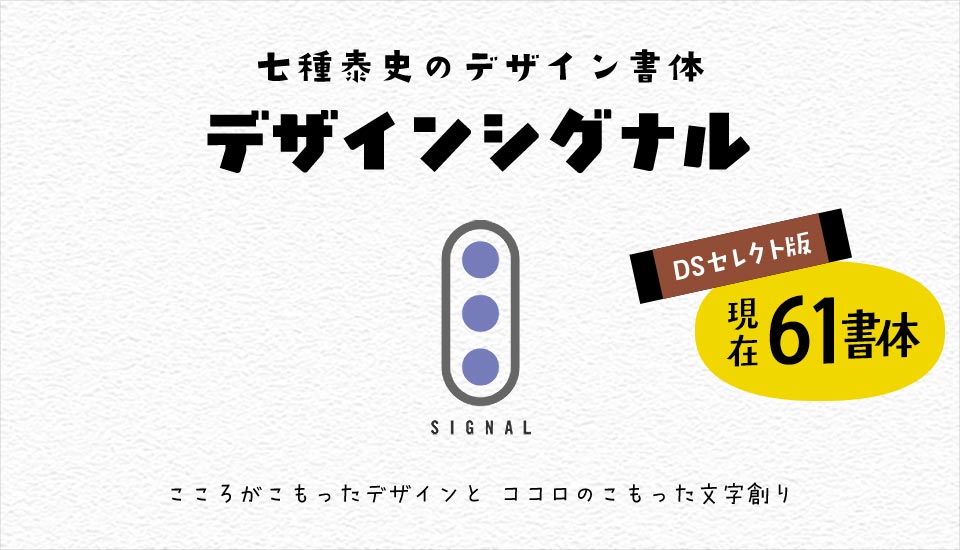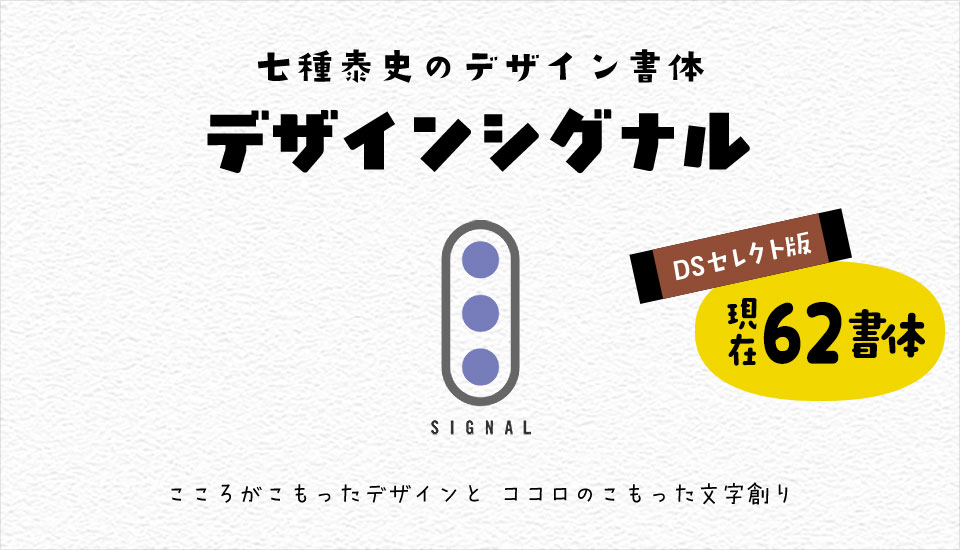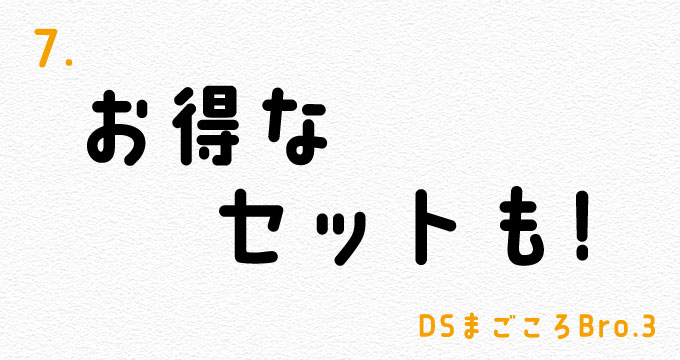
デザインシグナル・七種泰史のデザイン書体 DSセレクト版64書体
2026年秋の新書体「DS徒歩歩」が登場!
こころのこもった文字創りを目指すフォントブランドデザインシグナル。
2008年夏からオリジナルブランド・デザインシグナルセレクト版としてユーミンウォーク、トゥモローウォークを販売開始。現在も新作の開発が続いており、64書体を販売中です。お得なセット商品もご用意しております。
また、モリサワからはるひ学園、FONT1000ブランドからもウォークをはじめ17書体を発売。
七種泰史氏が世に送り出し、チラシやポスター、装丁、テレビCMなど、暮らしの中で見ない日はないと言っても過言ではないくらい非常に多くのデザイナーに愛される書体たちを一挙ご紹介!!
Adobe Fontsで提供されるADSシリーズとの違い
収録漢字数の違い
2025年2月よりAdobe Fontsにデザインシグナルから25書体が追加されました。Adobe Fontsで提供されるデザインシグナルの書体はフォント名がADSから始まり、フォント名がDSから始まる通常のデザインシグナルの書体とは別のフォントとして認識されます。
また、ADSシリーズの収録漢字が1,000文字なのに対し、デザインポケットで取り扱っているのDSシリーズは約3.4倍となる約3,409文字と大幅に充実しています。
デザインシグナル DSシリーズとAdobe Fontsで提供されるADSシリーズとの違い
※1 ADSシリーズは、常用漢字ベスト1,000文字。
※2 DSシリーズは、第1水準漢字2,965文字をフル収録。第2水準漢字も、日常的に頻用される444文字を収録しています。
収録漢字の違い (具体例)
下の見本で、緑色の文字は「DSシリーズ」にのみ収録されている漢字です。これらはAdobe Fontsで提供されている「ADSシリーズ」では使用できません。
デザインシグナル DSシリーズとAdobe Fontsで提供されるADSシリーズとの違い 具体例
下の画像で赤色の文字は、ADSシリーズ、DSシリーズに共通して収録されている漢字。緑色の文字は、DSシリーズにのみ収録されている漢字です。Adobe Fontsで提供されているADSシリーズでは収録漢字が3分の1以下となっています。
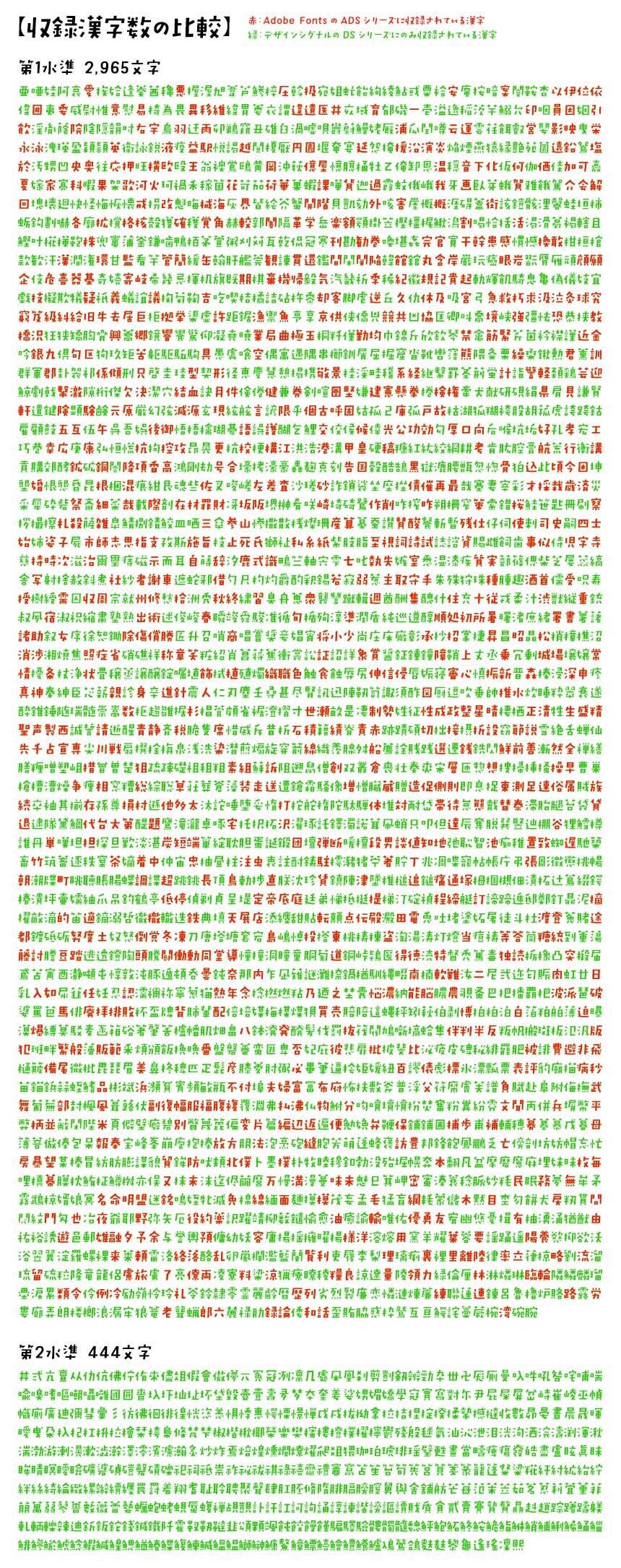
デザインシグナル DSシリーズとAdobe Fontsで提供されるADSシリーズとの違い 漢字一覧
七種泰史氏のオリジナルブランド「デザインシグナル」。2008年夏からスタートし、年に2~3書体のペースで開発を進行中。多くのファンが新作を心待ちにする人気のブランド。FONT1000版よりも多い全3,809文字を収録しています。レトロ感、可愛らしさ・愛らしさ、インパクト・存在感、個性が光る面白さなど、七種泰史氏ならではの世界観をご覧ください。
新書体「DS徒歩歩」
七種泰史/デザインシグナル
DS徒歩歩
軽やかに。楽しく明るく懐かしく
ゆっくり、ほっこりした書体です
あたたかく、懐かしい | DSきりぎりす
あたたかく、懐かしい。
レトロ、昭和、70年代、80年代。ホッとする懐かしさ。
いかにもデザインシグナルらしいフォルムの代表的7書体。
七種泰史/デザインシグナル
DSきりぎりす
切り文字のような大胆さを持ったデザインシグナルの一番人気
七種泰史/デザインシグナル
DSツリー
ほっこり、ゆっくり、あったか。軽やかで元気な書体です。
七種泰史/デザインシグナル
DS照和70
左ハライ同様に右も押さえず払い
手書きレタリングのような仕上げ
七種泰史/デザインシグナル
DS照和80
照和70をボリュームアップ
待望の太めレトロ書体
七種泰史/デザインシグナル
DSコリダンス
十分に個性的なのに主張しすぎない使い勝手のよい可愛らしさ
七種泰史/デザインシグナル
DSくるみるく
ふっくら、ほっこり
不揃いの中にも味のある書体
七種泰史/デザインシグナル
DS徒歩歩
軽やかに。楽しく明るく懐かしく
ゆっくり、ほっこりした書体です
律儀だけど親しみのある | DS歩明
カッチリした明朝体風エレメントもカジュアルな装いに。
力の抜けた雰囲気でも、キチンと感。
律儀だけど親しみのある印象の9書体。
七種泰史/デザインシグナル
DS歩明
歩くような速さの動き、よそ行きではない普段着の明朝体
七種泰史/デザインシグナル
DSユーミンウォーク
のほほんとした雰囲気、緊張感を和らげやさしい表情を醸し出す
七種泰史/デザインシグナル
DSフラミング
フラフラ + 明朝 + ハミング
パッと明るくなる楽しい雰囲気
七種泰史/デザインシグナル
DSそよ風
明朝タイプの軽やかデザイン、形もちょっぴり整って清々しい印象
七種泰史/デザインシグナル
DSなみ風
明朝タイプの軽やかデザイン、少しざわめく冒険心あふれる雰囲気
七種泰史/デザインシグナル
DS潮風
風シリーズの第三弾、そよ風・なみ風よりもしっかり太めな書体
七種泰史/デザインシグナル
DS青空
風シリーズの第三弾、そよ風・なみ風よりもしっかり太めな書体